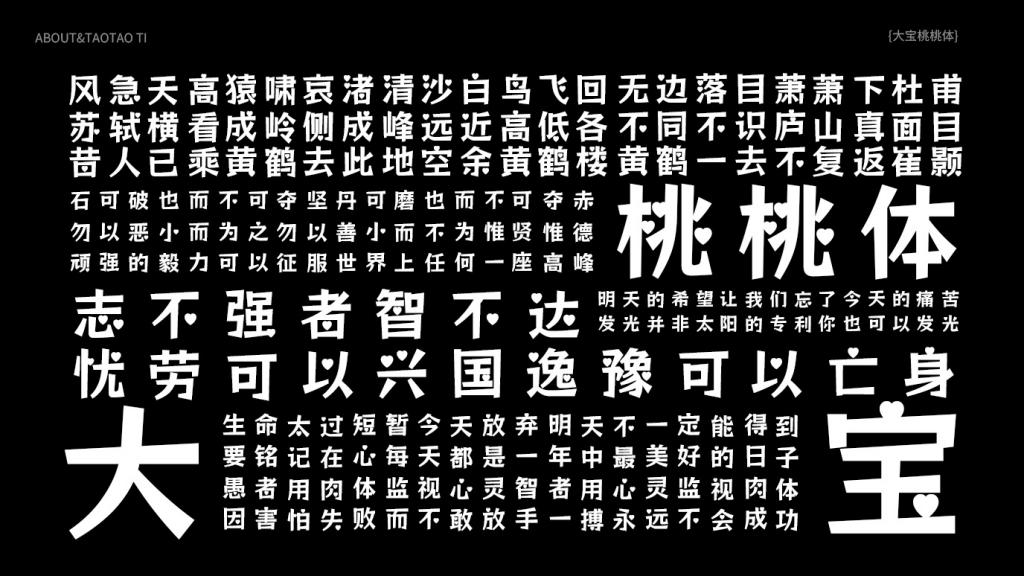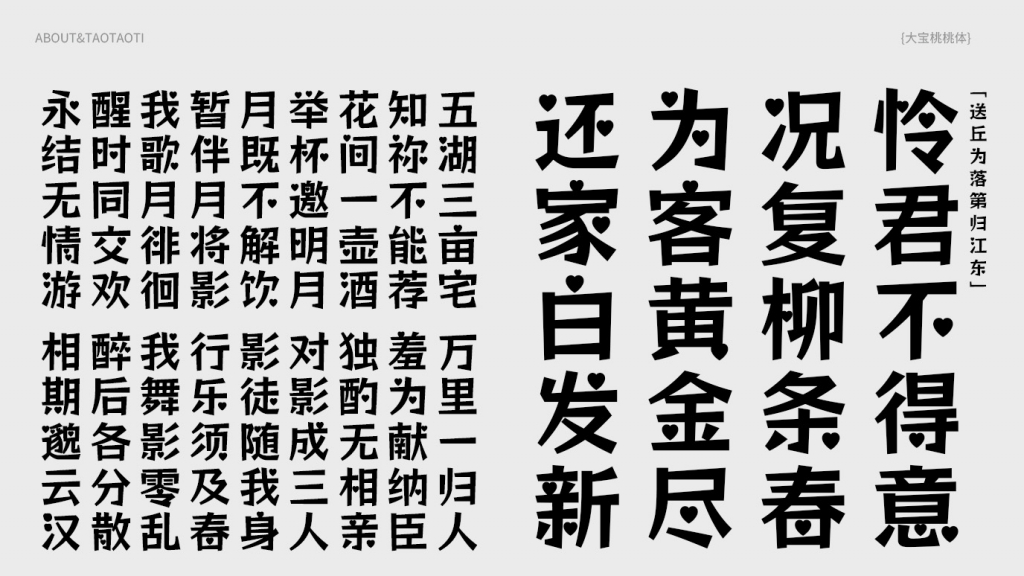
大宝桃桃体类似标小智龙珠体,为大宝知识星球制作的一款字体,把圆点部件换成爱心,整体显得可爱。十分适用于儿童,母婴产品以及萌系动画等场合,为此类场景增添天真可爱,无拘无束,自由自在的活力。这款字体除了用作标题,用于正文字体也有一种萌萌的感觉。
“大宝桃桃体”是一款书写很新颖的字体,字体大方,适合各种设计作品使用!欢迎下载!